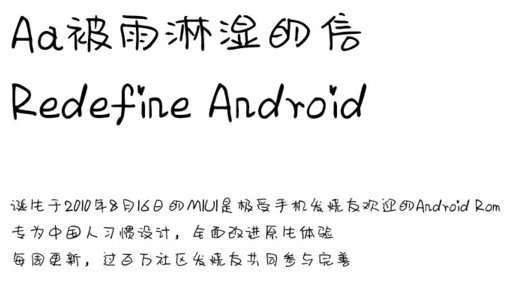
被雨淋濕的信字體是出自華為手機(jī)字體的一款有著特色修飾的手寫字體,將英文字母的圓點(diǎn)符號,變成可愛的愛心,給用戶帶來獨(dú)特的視覺享受,綠色資源網(wǎng)今日推薦!
被雨淋濕的信字體有著極其舒緩流暢的古風(fēng)韻味,線條柔軟而多姿,文字細(xì)膩而清和,有著極佳的藝術(shù)效果,給你的平面設(shè)計(jì)、包裝設(shè)計(jì)、海報(bào)制作、排版印刷等帶來不錯的增色!